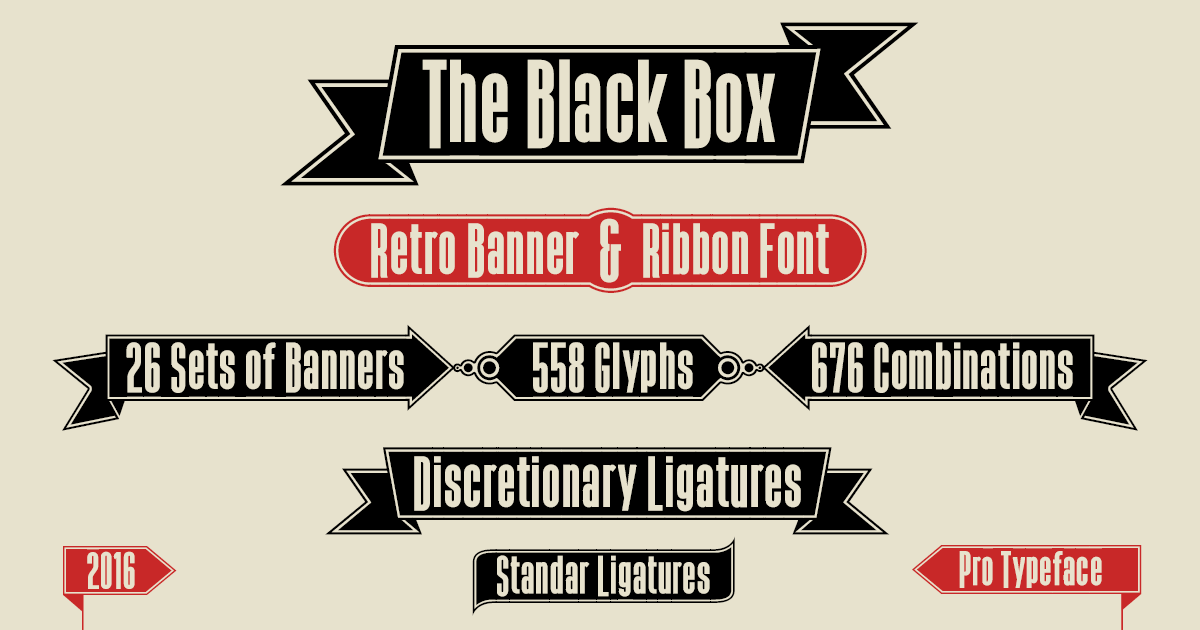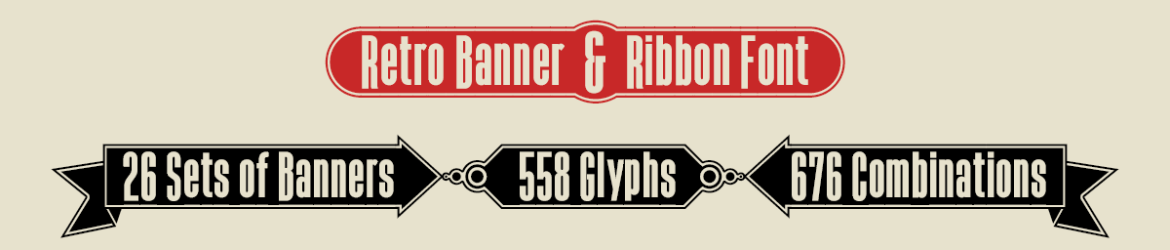
A fonte “The Black Box” é uma elegante escolha para designers que buscam um estilo sóbrio e contemporâneo, caracterizada por seu negritude condensada e um design minimalista ao redor de cada letra, criando o efeito de um retangular caixa. Essa configuração inovadora permite que você crie uma amplidão de padrões retro modernos, como banners e fitas, com seus 26 conjuntos de fechaduras da caixa oferecendo mais de 676 combinações possíveis para criar um estilo único e distintivo. Os símbolos ligados são igualmente úteis, fornecendo opções para a letra “b” que podem ser utilizadas em situações específicas, como os caracteres Bitcoin. O designer defharo trouxe uma riqueza de detalhes sem complexidades desnecessárias, criando um recurso gráfico versátil e sofisticado. Se você está procurando por uma fonte para criar designs futuristas ou retro, “The Black Box” é definitivamente uma opção a ser considerada. Além disso, a inclusão da licença completa do produto oferece mais liberdade de criação sem limitações de uso restritivas.